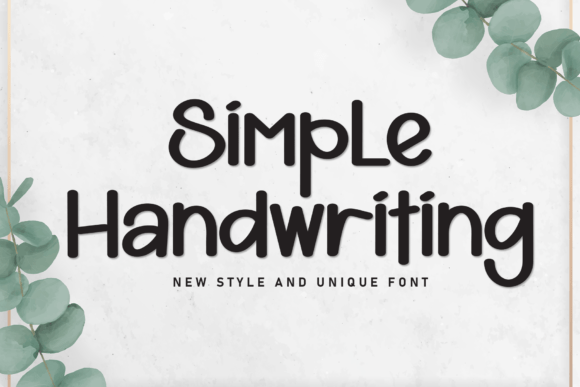
Simple Handwriting
Jika anda sedang mencari aset berkualiti tinggi seperti Simple Handwriting, pakej premium ini merupakan pilihan yang hebat untuk projek kreatif anda.
Sama ada anda mencipta produk POD (Print on Demand), jemputan perkahwinan atau grafik media sosial, Simple Handwriting amat bersesuaian.